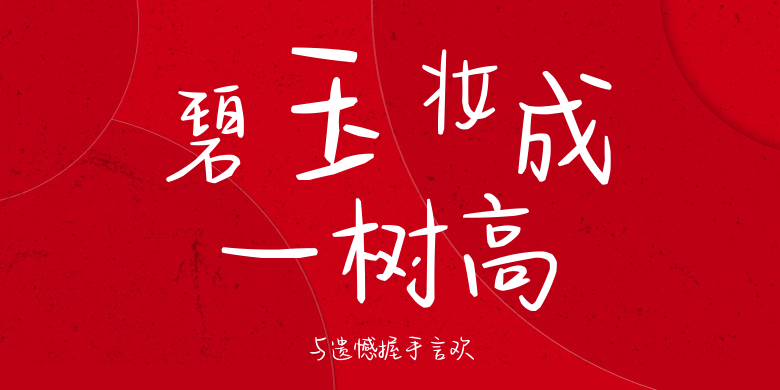
与遗憾握手言欢
与遗憾握手言欢,这款字体结构工整、笔画清晰,兼顾美观与易读性,适用于标题、正文、海报、包装、LOGO 等多种场景。字形优雅稳定,风格百搭耐看,适配日常排版与创意设计,让文字呈现更舒适、更具质感。与遗憾握手言欢一笔一画,皆是细节,以均衡的比例、流畅的线条打造舒适视觉体验,字形端正大气,风格简约现代。无论是商业设计、品牌宣传还是日常排版,都能轻松驾驭,让文字更有格调与力量。与遗憾握手言欢字体下载。